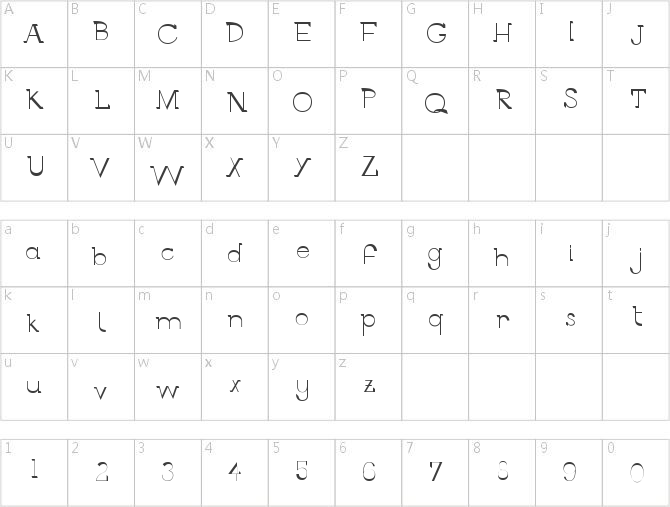
Berlin-Allee-SemiBold 詳情頁(yè)
Berlin-Allee-SemiBold字體字庫(kù)是一款讓人賞心悅目、百看不厭的英文字體,適合各類(lèi)廣告和產(chǎn)品包裝設(shè)計(jì)應(yīng)用,字體大小0.03MB,格式為ttf字體,上傳用戶(hù)是東方時(shí)尚,作者/版權(quán)方為未知